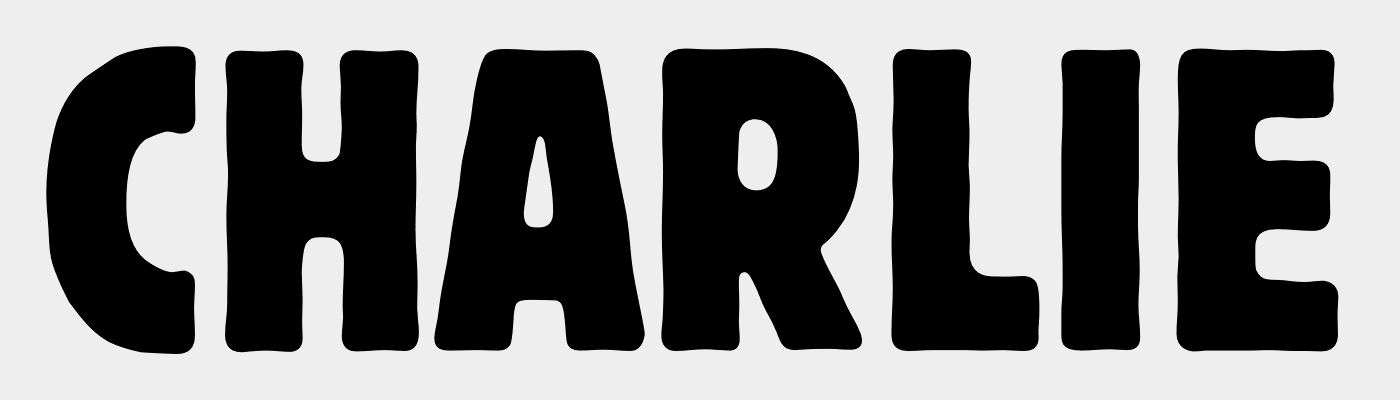
Kein politisches Statement, sondern ein neuer Font:
Schriftdateien sind die am längsten haltbare Software. Somit bleibt dieses kleine typografische Mahnmal bestehen, wenn die ersten Twitterkommentare schon wieder gelöscht wurden.
Mutige Aussage. Schriften, also die Formen an sich, sind haltbar, aber die Dateien als solche? Kann heute noch ein OSX etwas mit den MacOs-Schriftenkoffern anfangen? Oder wie war das Bangen, als ATM eingestellt wurde?
Dann hätte ich das aber auch in Form einer wirklich nutzbaren Schriftart gemacht, die man eben auch in Jahren moch verwenden möchte. Mit diesen "Demo-Transparent-Dingbats hat die Schrift eben auch nur die Lebensdauer der Twitter-Kommentare, wenn nicht sogar weniger.
Es geht m. E. ja nicht um die praktische Nutzbarkeit einer neu herausgebrachten Schrift, sondern um die einfache Möglichkeit seine Solidarität kundzutun. Sei es in Form einer kleinen Einschaltung in einem Medium oder als Aufkleber, Button etc.
Für diesen Zweck finde ich das eine originelle Idee.
Das wil ich auch gar nicht in Abrede stellen, nur ist eben der Claim, das ein Font per se langlebiger ist, als die Aktion, auf die er sich bezieht, wenn er nicht auch für andere Dinge nutzbar ist. In diesem Fall ist ein Font schon ein gutes Mittewl, um praktiosch jedem diese kleinen Vektorgrafiken zur Verfügung zu stellen, aber es ist eben trotz allem eine kurzlebige Sache, mHäte man eiunen WTC911-Font heraus gebracht, würde den, enthielte er solche Solidaritäts-Botschaften auch kaum noch jemand hervor kramen.
Und die nutzbaren Schriften gibt es schon, aber die heißen nun mal nicht "je suis Charlie" Hätte man sich jetzt eine Schriftart genommen, die regulär als Satz- oder Displayschrift nutzbar ist, dann wäre die Chance groß, das diese dann auch in Jahrenb noch eingesetzt wird, und so "je suis Charlie" auch in Erinnerung bleibt, aber niemand wird beider Verwendung von Bliock Berthild Condended oder Sweet Sans Heavy an "je suis Charlie" denken.
Auf mich wirkt es eher wie Marketing für das Büro … umsonst einmal durch alle Blogs und Foren.
Ob Font oder nicht Font, bleibt die Frage wie sinnreich die »ich bin Charlie« Aktion in allen Varianten ist. Bei den Überlebenden kam die Aktion wohl auch nicht immer gut an („Wir kotzen im Strahl auf all diese Leute, die auf einmal unsere Freunde sein wollen.)
Naja, aber immerhin hat sie Stoff für das Titelbild der neuen Ausgabe geliefert (der Prophet mit einem umgehängten »Je suis Charlie« Schild unter der Titelzeile: tout est pardonée – alles ist vergeben). Das wird wohl bleiben.
PS: So hat die Titanic-Redaktion ihre Anteilnahme ausgedrückt